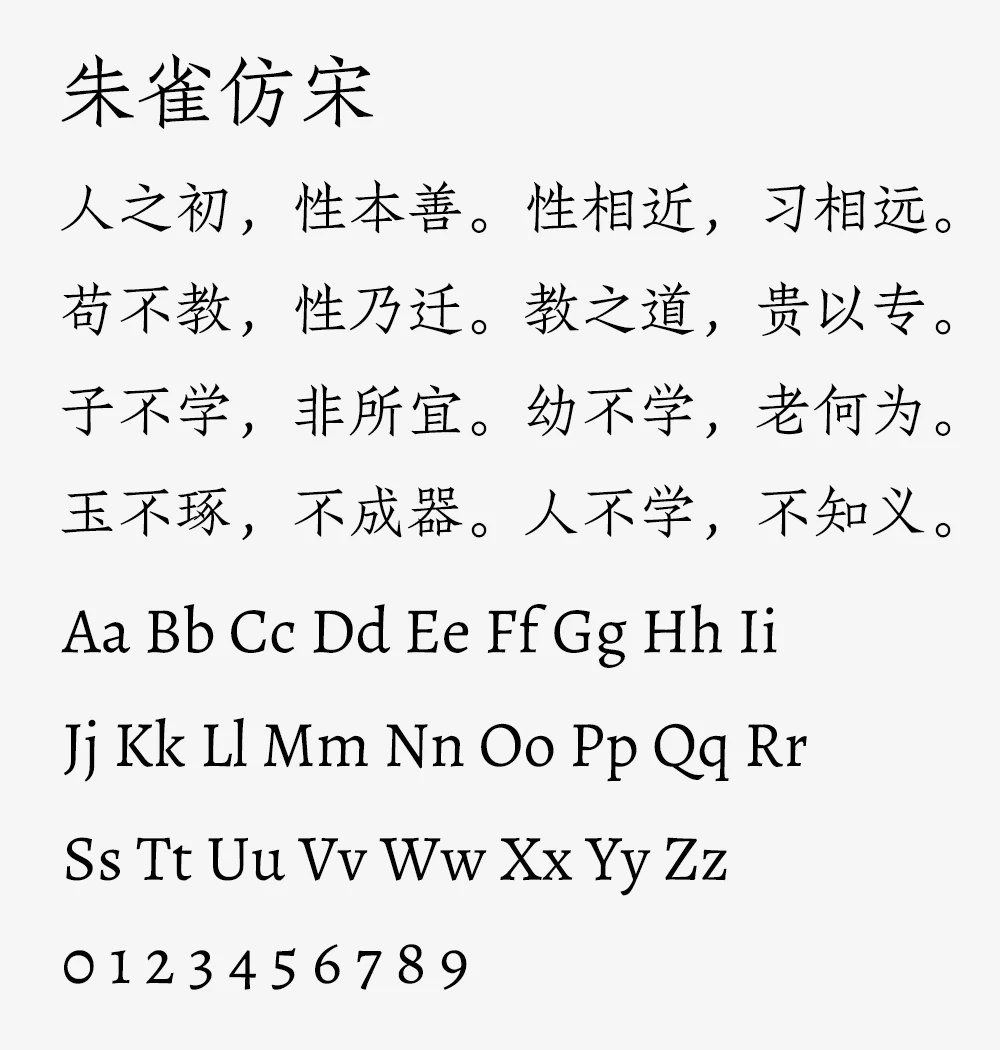
朱雀仿宋(Zhuque Fangsong)是由国内造字品牌璇玑造字(TrionesType 团队)开发的一款免费开源的仿宋字体。主要是为了填补中文四大基础字体(宋、黑、仿、楷)中仿宋体在开源领域的长期空白。
它是以民国时期著名的仿宋活字「南宋」为基础,由韩佑之设计原稿,邹根培雕刻字模,再结合AI辅助完成衍生字形才最终成型。既保留了传统仿宋的韵味,又满足了现代排印需求,为开源软件与 TeX 排版社区提供了专业级的正文仿宋解决方案。
目前朱雀仿宋仍处于预览测试阶段,但已覆盖《通用规范汉字表》一、二级,总汉字数达 6512 字,完全可以满足日常使用需求。而且仿宋体本身就是介于宋体与楷书之间的一种印刷字体,也是国家标准 GB/T 9704-2012 推荐的中文字体,所以常用在政府公文、古籍排版、学术出版等正式场景。